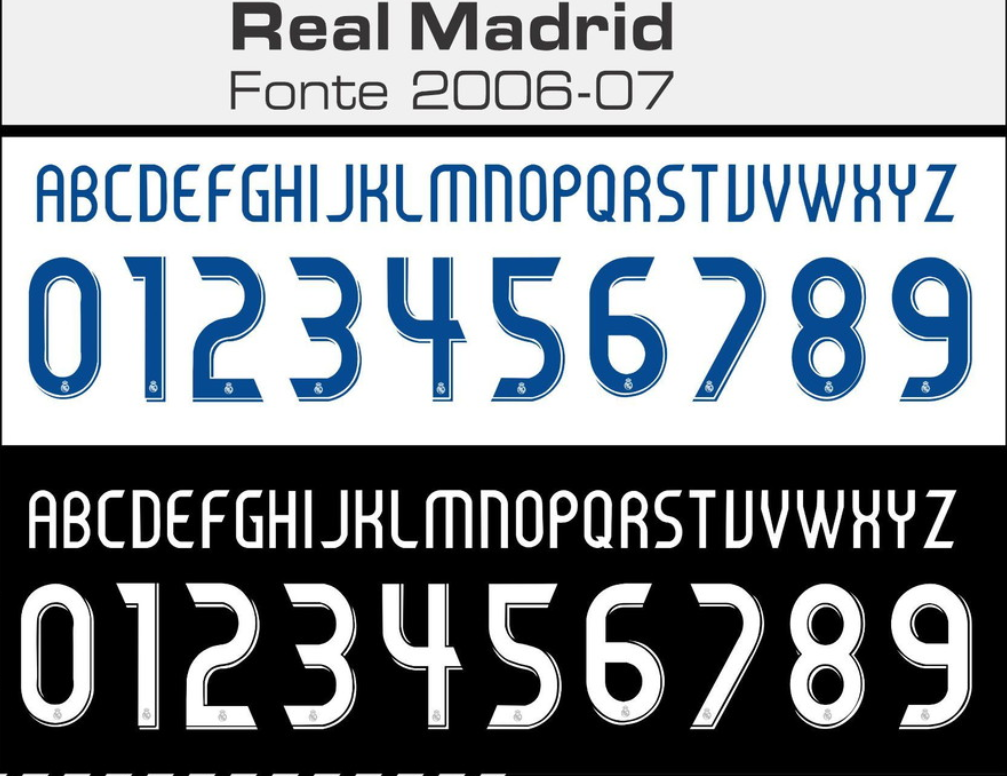
Viaje no tempo para uma das eras mais icônicas do futebol mundial. A temporada 2006-2007 marcou a história dos Merengues não apenas pela conquista dramática de La Liga sob o comando de Fabio Capello, mas também pelos uniformes clássicos assinados pela Adidas.
Esta fonte carrega o peso de lendas. Foi com essa tipografia nas costas que craques como David Beckham, Ruud van Nistelrooy, Ronaldo Fenômeno, Raúl e Roberto Carlos brilharam no Santiago Bernabéu. Se você busca restaurar uma camisa vintage ou criar designs com a estética “Teamgeist” da época, este arquivo é indispensável.
- Conteúdo: Alfabeto completo e numeração oficial da época.
Estilo Visual e Aplicação
A fonte utilizada pela Adidas na temporada 06/07 reflete o design dinâmico daquela década. Diferente das fontes minimalistas atuais, a tipografia do Real Madrid neste ano apresentava curvas suaves e uma estrutura arredondada, típica da linha Teamgeist que dominou a Copa do Mundo de 2006.
Ela se destaca pela excelente legibilidade e pelo estilo robusto. Foi aplicada originalmente na cor preta sobre o uniforme titular branco (Home Kit) e na cor branca sobre o uniforme reserva preto ou roxo. É uma fonte que transmite classe e nostalgia imediata para qualquer fã de futebol europeu.
Dica de Ouro: Para um realismo total na sua personalização, lembre-se que o logo da Real Madrid (o escudo pequeno) costumava ser aplicado na base dos números nessa temporada.